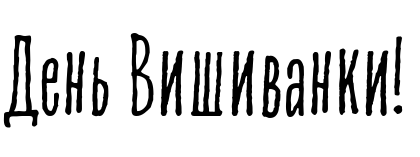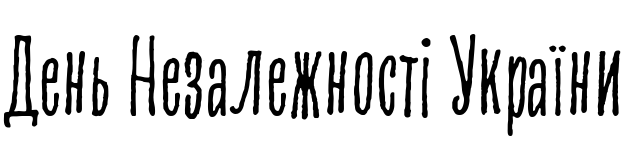
Асоціації зі шрифтом Six Hands RoughОсобистість і характер шрифта:
домашній, теплий, ручний, натуральний, природний, смачний, екологічний, апетитний, рукотворний, кустарний, саморобний, високий, оригінальний, модний, живий, характерний, грайливий, ламповий, органічний, крафтовий, грубий, рослинний, лісовий, кріповий, тісний, самобутній, непосидючий, неслухняний, ремісничий, фермерський, стрибучий, хуліганський, осінній, дивний, божевільний, стиснений, економічний, артізанальний, макабричний, випадковий